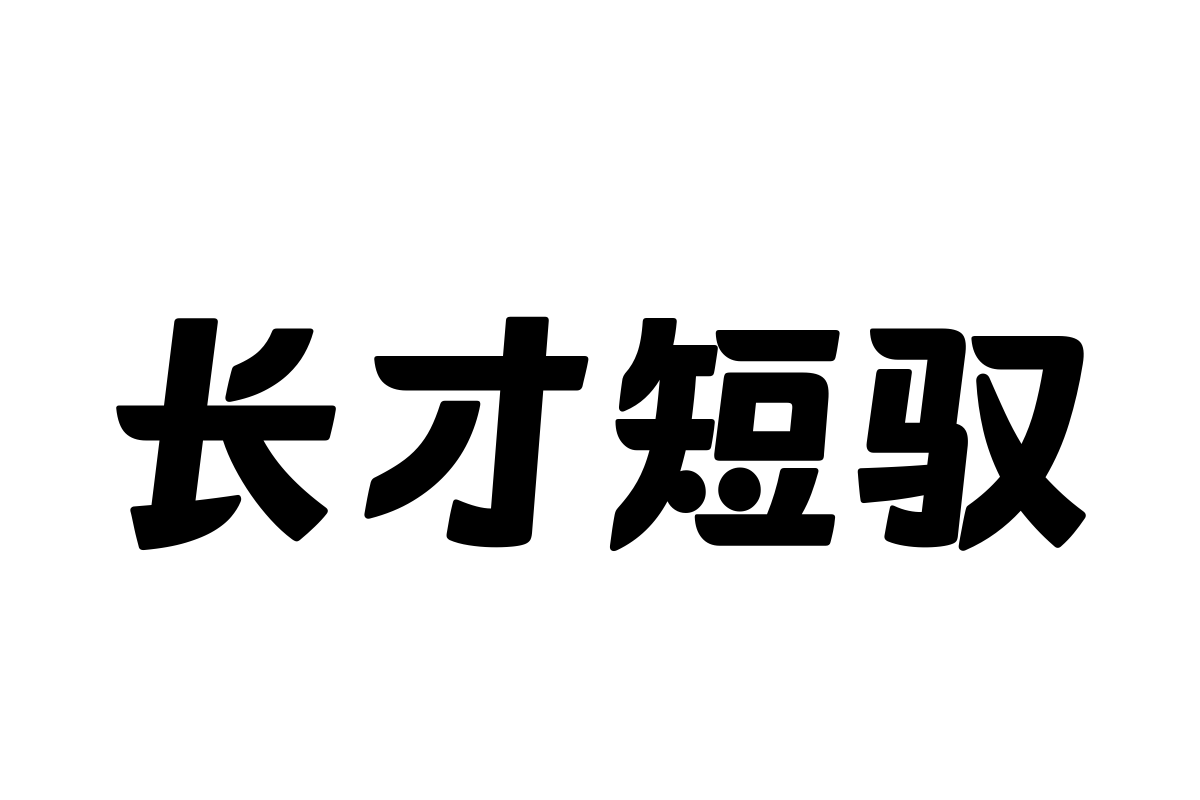
汉仪大白兔字体是一款现代感十足的中文字体,具有独特的设计风格和特点。该字体采用了简洁的线条和形状,给人一种清新、简约的感觉。它的笔画粗细适中,既有力度又有弹性,既适合用于标题、正文等需要突出显示的部分,也适合用于一些较为正式或商务性质的文本中。
此外,汉仪大白兔字体还具有一定的可读性,无论是在电脑屏幕上还是印刷品上都能保持良好的视觉效果。它的设计灵感来自于传统的汉字书法艺术,通过简化笔画和结构,使得整个字体更加易于识别和阅读。
总的来说,汉仪大白兔字体是一款非常适合用于各类文本设计的字体,无论是广告、海报还是其他宣传材料,它都能为你的作品增添一份独特的魅力。